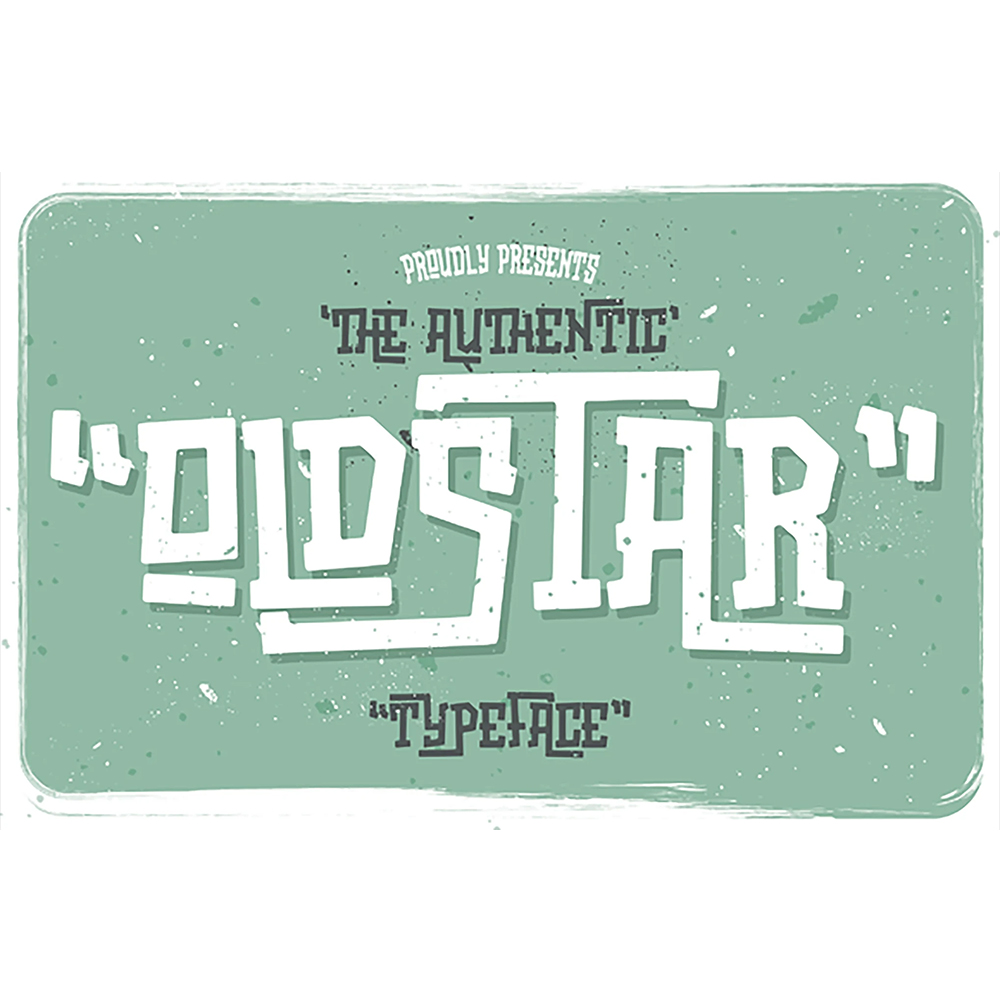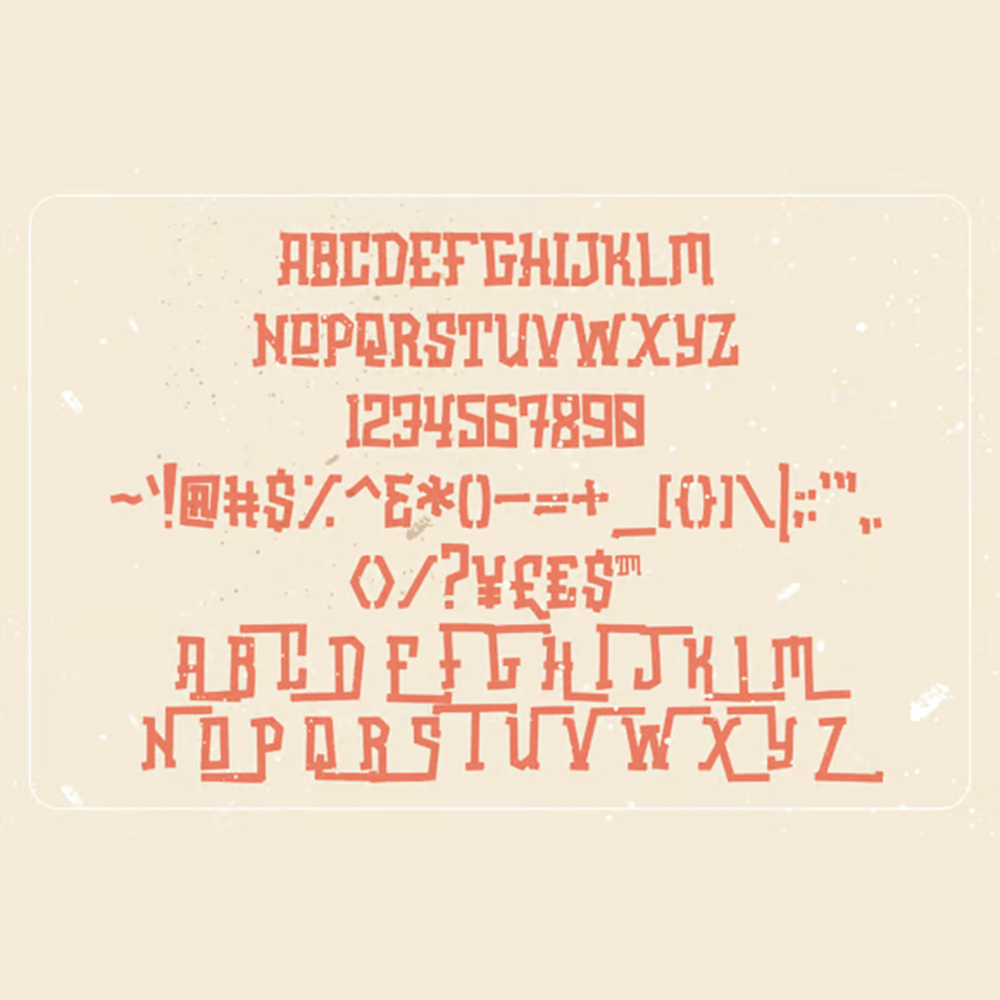
دانلود فونت انگلیسی Oldstar Font
فونت پرمیوم و انگلیسی Oldstar Font به دوستداران فرهنگ شخصیسازیشده تقدیم شده است. فونتهای قدیمی و قدیمی منابع اصلی الهامبخش برای خلق این فونت هستند. میتوانید از این فونت برای خلق یک لوگو با لیگاتور، سبک خاص استفاده کنید و به راحتی میتوانید این فونتها را به هر شکلی که دوست دارید تغییر دهید، به این امید که خوشایند باشد.
مزایای استفاده از فونت لاتین Oldstar چیست؟